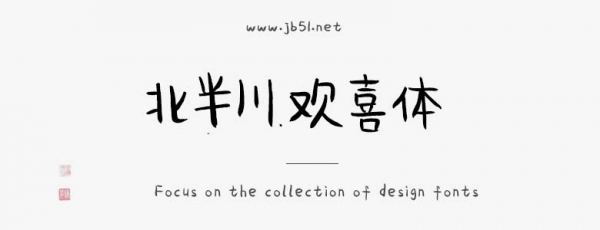
北半川歡喜體是一款不錯(cuò)的藝術(shù)字體,字體筆觸略細(xì),書寫流暢,具有很好的視覺感,適合應(yīng)用于藝術(shù)設(shè)計(jì)、平面宣傳設(shè)計(jì)、網(wǎng)頁(yè)設(shè)計(jì),書法字帖等領(lǐng)域,需要的朋友可以前來(lái)本站下載。